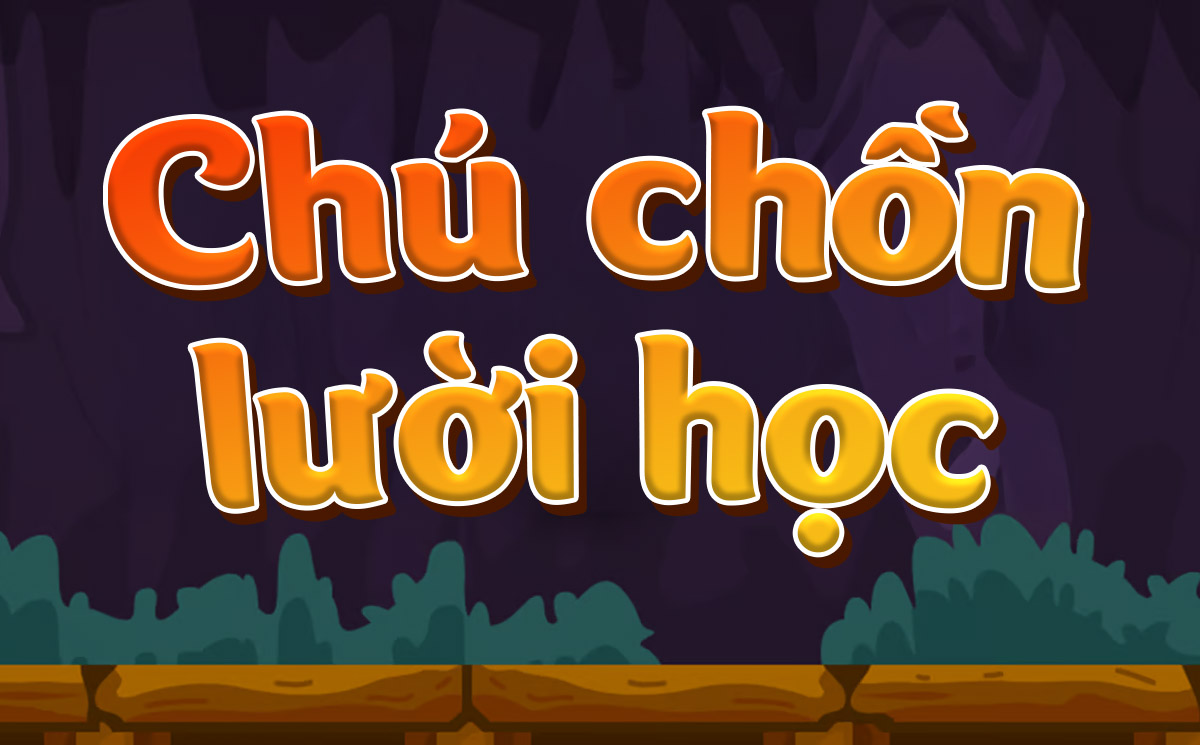
Font chữ hoạt hình mũm mĩn cute Việt hóa SVN Gumley
Font chữ hoạt hình mũm mĩn cute Việt hóa SVN Gumley là sự lựa chọn hoàn hảo dành cho các nhà thiết kế đang tìm kiếm phong cách vui nhộn, tươi sáng và tràn đầy năng lượng tích cực. Được tinh chỉnh tỉ mỉ theo hệ thống bảng chữ cái tiếng Việt, bộ font này giúp các tác phẩm đồ họa thiếu nhi, bao bì sản phẩm và ấn phẩm truyền thông trở nên sống động, gần gũi hơn bao giờ hết. Đây chắc chắn là giải pháp typography không thể bỏ qua để tạo nên điểm nhấn thị giác ngọt ngào và cuốn hút người xem ngay từ ánh nhìn đầu tiên.
Font Chữ Hoạt Hình Mũm Mĩn Cute Việt Hóa SVN Gumley – Giải Pháp Typography Sáng Tạo Cho Thiết Kế Đáng Yêu
Trong thế giới thiết kế đồ họa đa dạng ngày nay, việc lựa chọn font chữ phù hợp đóng vai trò quyết định đến cảm xúc và thông điệp mà ấn phẩm truyền tải. Các xu hướng thiết kế mang hơi hướng ngộ nghĩnh, tươi vui đang ngày càng chiếm lĩnh thị trường, đặc biệt trong các ngành hàng tiêu dùng nhanh, giáo dục, thời trang trẻ em và truyền thông số. Nổi bật giữa hàng loạt kiểu chữ hiện đại, font chữ hoạt hình mũm mĩn cute Việt hóa SVN Gumley mang đến một làn gió mới đầy mê hoặc, giúp mọi ý tưởng sáng tạo trở nên ngọt ngào và đậm chất nghệ thuật hoạt họa.
SVN Gumley là phiên bản Việt hóa công phu từ phông chữ gốc Gumley nổi tiếng, được chăm chút kỹ lưỡng từng đường cong, nét uốn lượn để phù hợp hoàn hảo với ngữ pháp và hệ thống dấu thanh tiếng Việt. Font chữ không chỉ giải quyết triệt để vấn đề lỗi font dấu khi gõ tiếng Việt mà còn giữ trọn vẹn tinh thần phóng khoáng, dễ thương của bản thiết kế ban đầu.
1. Thiết kế nét chữ bo tròn mũm mĩn đậm chất hoạt hình vui nhộn
Điểm nhấn đắt giá nhất của SVN Gumley chính là cấu trúc hình thể mập mạp, các góc cạnh được bo tròn mềm mại tựa như những viên kẹo dẻo ngọt ngào hay những đám mây bồng bềnh. Mỗi ký tự đều toát lên vẻ ngoài đáng yêu, tràn đầy sinh khí, mang lại cảm giác thân thiện và xua tan sự cứng nhắc thường thấy ở các kiểu font truyền thống. Từng đường nét dày dặn giúp phông chữ có độ nhận diện cao, nổi bật trên mọi nền màu sắc và dễ dàng thu hút sự chú ý của người xem, đặc biệt là đối tượng trẻ em và giới trẻ gen Z.
2. Hệ thống dấu tiếng Việt được tối ưu hóa chuẩn chỉnh và tinh tế
Một trong những thách thức lớn nhất khi sử dụng font chữ nước ngoài theo phong cách hoạt hình là sự mất cân đối khi gõ tiếng Việt. Đối với SVN Gumley, đội ngũ Việt hóa đã xử lý công phu từng dấu sắc, huyền, hỏi, ngã, nặng cũng như các dấu mũ, dấu móc của các nguyên âm như ă, â, ê, ô, ơ, ư. Toàn bộ dấu thanh đều được căn chỉnh độ cao, tỷ lệ và độ dày sao cho đồng bộ hoàn hảo với dáng chữ mũm mĩn của thân ký tự. Điều này đảm bảo bố cục văn bản luôn liền mạch, đẹp mắt và không xuất hiện hiện tượng đè dấu hay khoảng cách chữ bị rời rạc.
3. Ứng dụng linh hoạt và đa dạng trên nhiều lĩnh vực thiết kế
Font chữ hoạt hình mũm mĩn cute SVN Gumley sở hữu tính ứng dụng vô cùng phong phú, đáp ứng trọn vẹn nhu cầu sáng tạo trong nhiều dự án khác nhau:
• Thiết kế bao bì và nhãn dán: Phù hợp cho các sản phẩm bánh kẹo, đồ uống ngọt ngào, đồ chơi thiếu nhi, mỹ phẩm organic hay các sản phẩm handmade yêu cầu sự gần gũi, ấm áp.
• Ấn phẩm truyền thông số: Tạo tiêu đề bắt mắt cho ảnh bìa YouTube, thumbnail video TikTok, bài đăng mạng xã hội, banner quảng cáo khuyến mãi dành cho giới trẻ.
• Thời trang và quà tặng: Ứng dụng in ấn áo thun hoạt hình, túi tote, thiệp chúc mừng sinh nhật, sổ tay lưu niệm và sticker trang trí.
• Sách báo và truyện tranh: Sử dụng làm tiêu đề chương, bìa sách thiếu nhi, truyện tranh vui nhộn hay bảng thông báo tại các trường mầm non.
5. Gia tăng trải nghiệm thị giác và kích thích cảm xúc tích cực của khách hàng
Về mặt tâm lý học thị giác, các đường nét bo cong và dáng vẻ mũm mĩn thường kích hoạt cảm giác an toàn, vui tươi và dễ mến trong tâm trí khách hàng. Việc sử dụng SVN Gumley trong bộ nhận diện thương hiệu hoặc chiến dịch tiếp thị giúp thương hiệu xóa bỏ khoảng cách với người tiêu dùng, tạo dựng hình ảnh trẻ trung, năng động và giàu tính nhân văn. Đây là vũ khí đắc lực giúp nâng cao tỷ lệ tương tác và để lại ấn tượng sâu đậm trong lòng khách hàng mục tiêu.
Bí quyết phối màu và hiệu ứng ấn tượng với SVN Gumley
Để font chữ SVN Gumley phát huy tối đa sức hút thị giác, bạn có thể áp dụng một số mẹo thiết kế sau:
• Bảng màu ngọt ngào (Pastel & Candy Colors): Kết hợp chữ với các gam màu như hồng phấn, vàng bơ, xanh mint, cam đào hoặc tím lavender để tăng cảm giác ngọt ngào, tươi mới.
• Tạo hiệu ứng 3D dạng kẹo/thạch: Thêm viền trắng dày bên ngoài kết hợp lớp bóng đổ đa tầng (pop-art style) để biến các dòng tiêu đề thành những khối chữ nổi bật như phim hoạt hình 3D.
• Kết hợp font chữ tương phản: Sử dụng SVN Gumley cho các tiêu đề chính (Heading) và kết hợp cùng các font sans-serif tròn trịa, thanh mảnh cho phần nội dung chi tiết (Body text) nhằm tạo sự cân bằng và dễ đọc cho người xem.
Tóm lại, font chữ hoạt hình mũm mĩn cute Việt hóa SVN Gumley là một công cụ sáng tạo xuất sắc mà bất kỳ designer, content creator hay chủ shop kinh doanh nào cũng nên sở hữu trong bộ sưu tập typography của mình. Với nét vẽ ngộ nghĩnh, sự tinh tế trong từng dấu tiếng Việt cùng khả năng ứng dụng đa dạng, SVN Gumley chắc chắn sẽ biến mọi ý tưởng thiết kế của bạn trở nên sống động, đáng yêu và đầy sức hút.